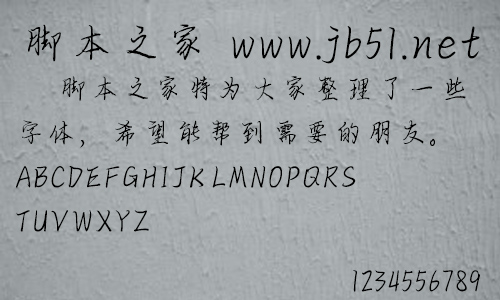
冬日戀歌是一款十分不錯(cuò)的藝術(shù)字體,這款字體筆觸較為詳細(xì),書(shū)寫(xiě)隨性灑脫,具有很好的視覺(jué)感,適合應(yīng)用于藝術(shù)設(shè)計(jì)、平面宣傳設(shè)計(jì)、網(wǎng)頁(yè)設(shè)計(jì),書(shū)法字帖等領(lǐng)域胡。需要的朋友不要錯(cuò)過(guò)哦!